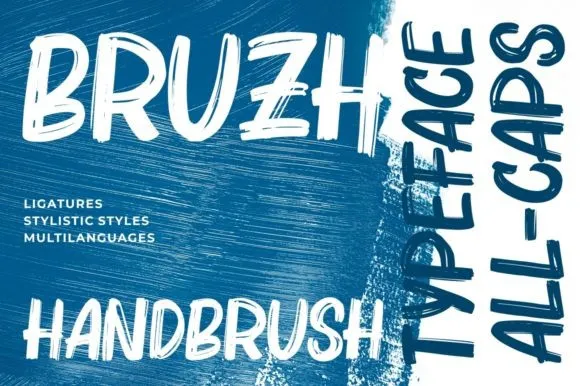
Bruzh Brush Font – Fonte Grátis
Bruzh Brush Font
Aqui está uma versão em português para a descrição da fonte ‘Bruzh Brush Font’, seguindo as regras fornecidas: Estamos muito felizes por você ter acionado Bruzh Brush Font, uma elegante e vibrante fonte script de letra à mão. Desenhada pelo talentoso designer f0rdesigner, ela traz o realismo da tinta desidratada ao papel com um toque natural e quase áspero. As linhas suaves e vivas remetem a uma paleta de sentimentos fortes, desde energia até tranquilidade. Esta fonte é perfeita para personalizar suas campanhas promocionais, seja em promoções online ou impressas. Ela também se destaca na internet, destacando-se nas publicações de Instagram e Stories, nas identidades visuais de marcas, nas capas de livros e revistas, nos convites de casamento, embalagens, desfiles de moda, cartões de aniversário ou em qualquer tipo de projeto que exija um toque autêntico. Bruzh Brush é o ideal para ilustrar uma frase principal, criar uma identidade visual única ou adicionar um toque especial a um trabalho de arte, garantindo sempre um toque autoral e imediato. A fonte fala por si só sobre seu potencial, tornando cada projeto mais único e memorável.